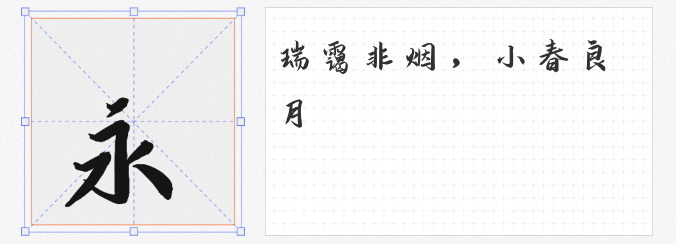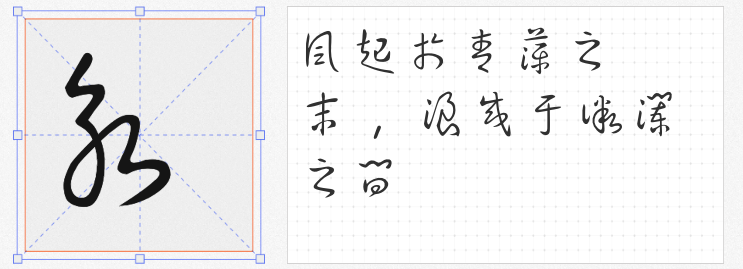
在追求个性化表达的设计领域,书法字体以其独特的艺术魅力成为设计师的灵感源泉。本期推荐四款兼具文化底蕴与创意巧思的免费商用书法字体,它们以手写感为魂,以实用性为骨,为设计作品注入传统韵味与现代活力的双重基因。
1.【寒蝉龙藏楷书 Bold】
脱胎于开源字体「有字库龙藏体」,这款加粗版楷书如墨色凝练的碑刻,在保留传统楷书端庄骨架的基础上,通过笔触的强化处理,赋予文字雄浑厚重的视觉张力。其拓展字形覆盖多场景需求,尤其适合品牌标题或文化类海报设计,既能承载历史厚重感,又能彰显现代设计的力量美学。
2.【演示悠然小楷】
这款小楷字体堪称阅读友好型典范,笔画如竹简刻痕般分明,结构如星斗排列般清晰。摒弃繁复连笔与飞白装饰,专注文字信息传递的本质,天然疏朗的字间距使其成为长文案设计的理想选择。无论是书籍内页、网页正文,还是导视系统,都能营造舒适从容的阅读体验。
3.【草书 简入繁出】
由民间书法爱好者精心打磨的狂草字体,以孙过庭书风为蓝本,将草书的写意精神转化为17000余个规范字符的奇迹。其字形简而不单,繁而不乱,既保留「癫张醉素」的狂放气韵,又实现数字化时代的精准应用。特别适合古籍研究、文创产品开发,让传统书法在数字世界焕发新生。
4.【台湾教育部标准隶书】
作为官方认证的权威字体,这款隶书以《教育部隶书母稿》为源,历经多次修缮终成典范。4808个国标字符严循规范,既保留隶书的蚕头燕尾之韵,又兼具现代印刷体的清晰辨识度。适用于教育出版物、政府公文等正式场景,让经典书体成为文化传承的坚实载体。
这四款字体如同四卷风格迥异的墨色长卷,既为设计师打开传统书法的宝库,又提供灵活多变的创意解决方案。从碑刻雄风到信笺雅意,从狂草纵情到官书严谨,它们跨越时空的书写智慧,正等待着在数字画布上绽放新的生命。